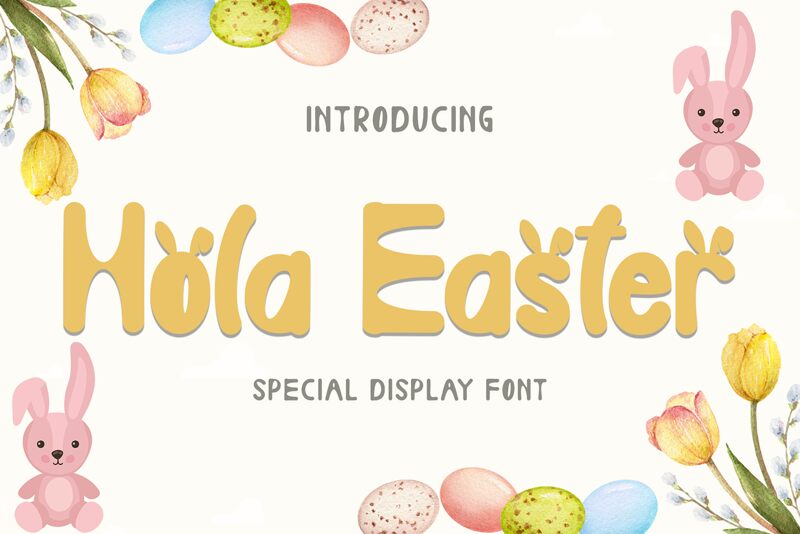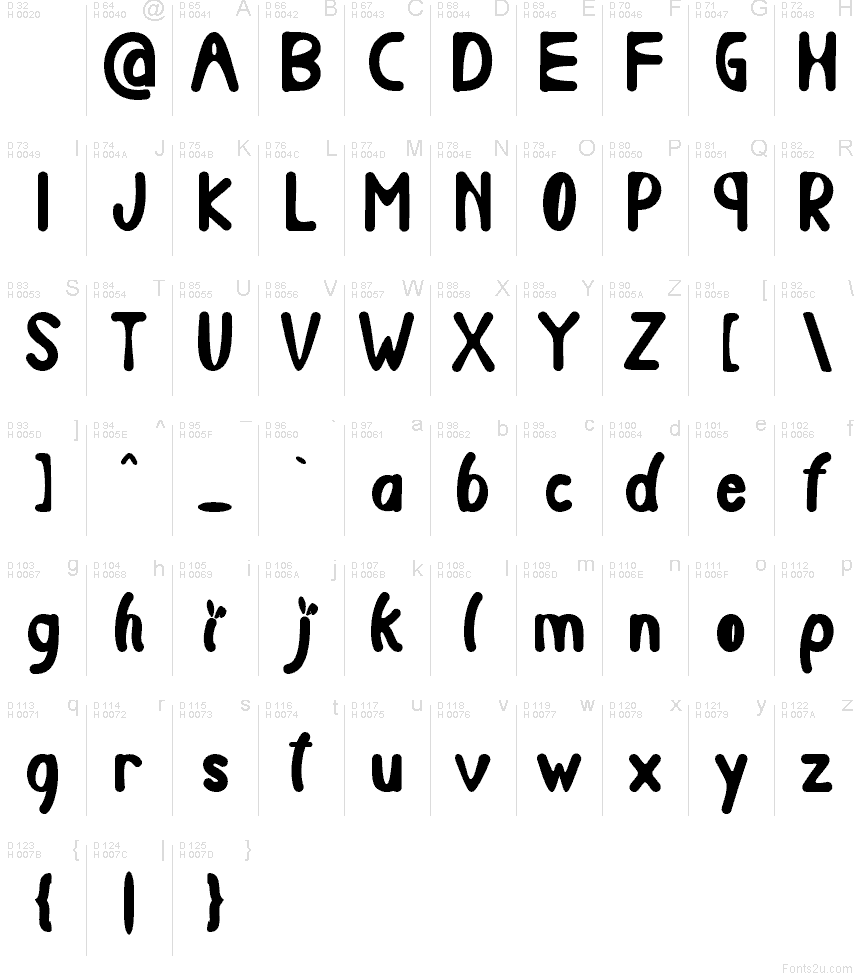
Hola Easter
Hola Easter de Yoga Letter es una tipografía display gratuita con formas redondeadas y trazadas a mano que fluyen con suavidad. Sus letras se sienten amplias y relajadas, combinando trazos altos y fluidos con formas compactas, lo que le otorga un aire amable y festivo, ideal para la época de Pascua sin necesidad de adornos excesivos.
Hola Easter funciona de maravilla en invitaciones, banners primaverales, tarjetas de felicitación, títulos de pósteres, folletos de eventos y gráficos para redes sociales, ya que sus curvas mantienen un estilo cercano e informal. Esta tipografía gratuita también es perfecta para detalles en packaging, etiquetas artesanales y citas decorativas cuando buscas un diseño temático que se sienta natural y hecho a mano.